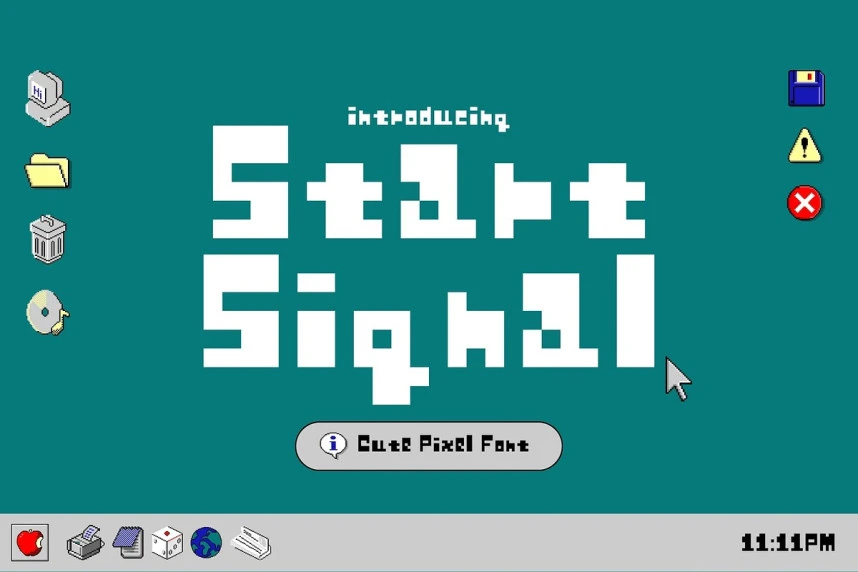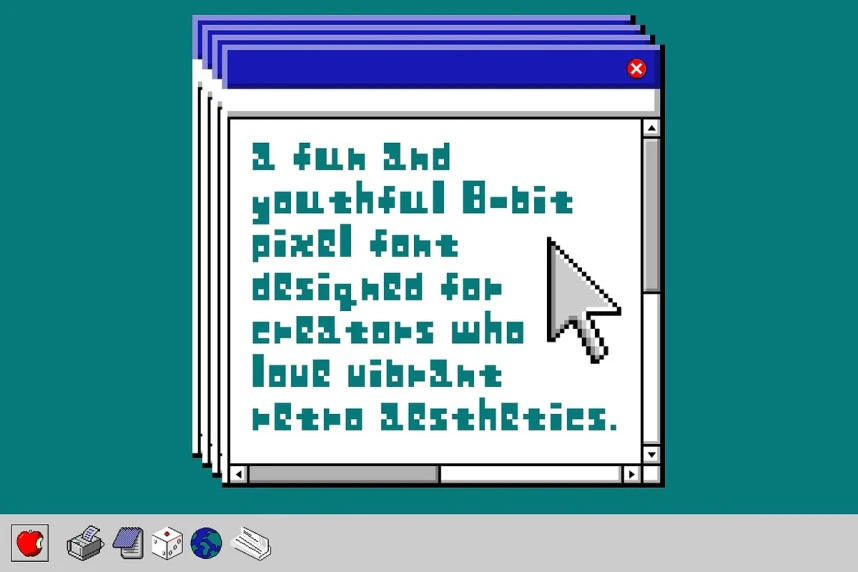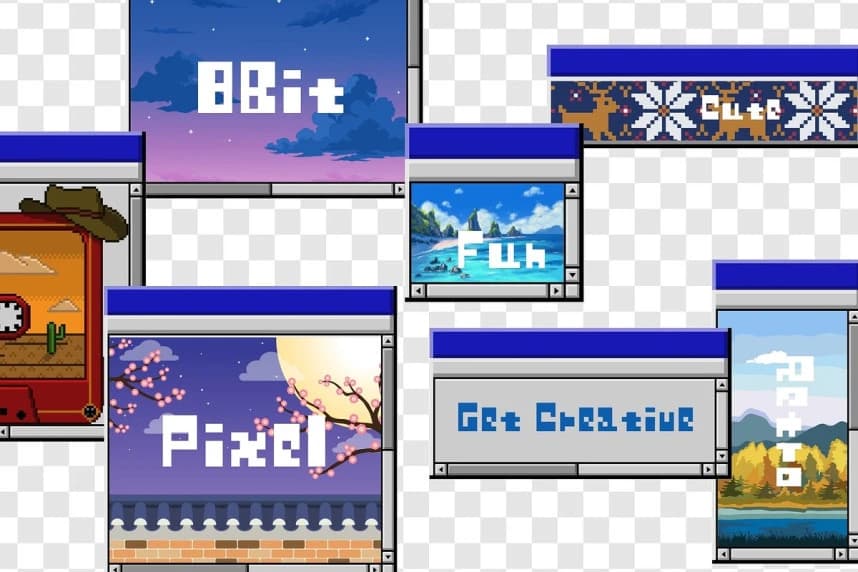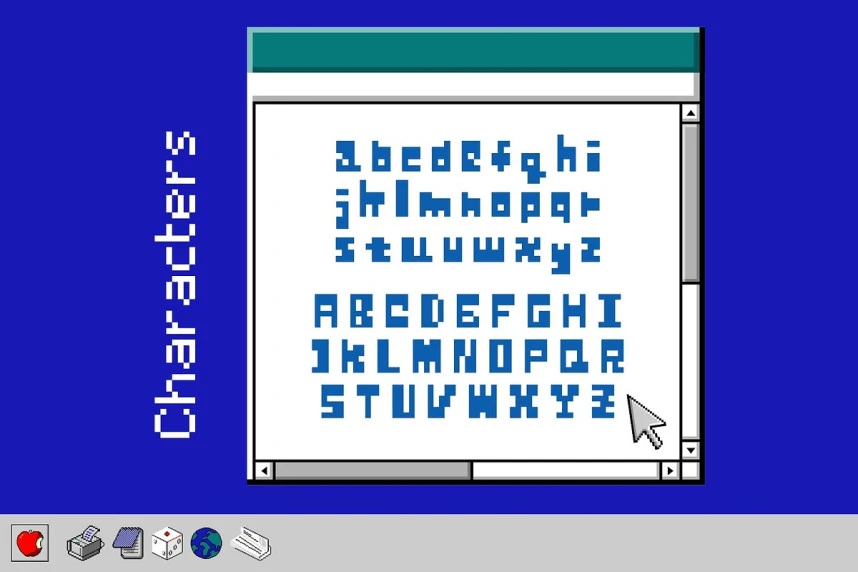
Start Signal Font
Start Signal Font, canlı ve genç bir 8-bit piksel yazı tipidir; retro estetiği seven yaratıcılar için tasarlanmıştır. Keskin piksel kenarları, oyunbaz karakter şekilleri ve enerjik dijital kişiliğiyle bu yazı tipi, klasik arcade cazibesini modern piksel stili projelere taşır.
Start Signal Font, canlı retro estetiğini seven yaratıcılar için tasarlanmış eğlenceli ve genç bir 8-bit piksel yazı tipidir. Keskin piksel kenarlarına, oyunbaz karakter şekillerine ve enerjik bir dijital kişiliğe sahip olan bu yazı tipi, klasik arcade cazibesini modern piksel stilindeki projelere taşır.
Start Signal
Start Signal Regular